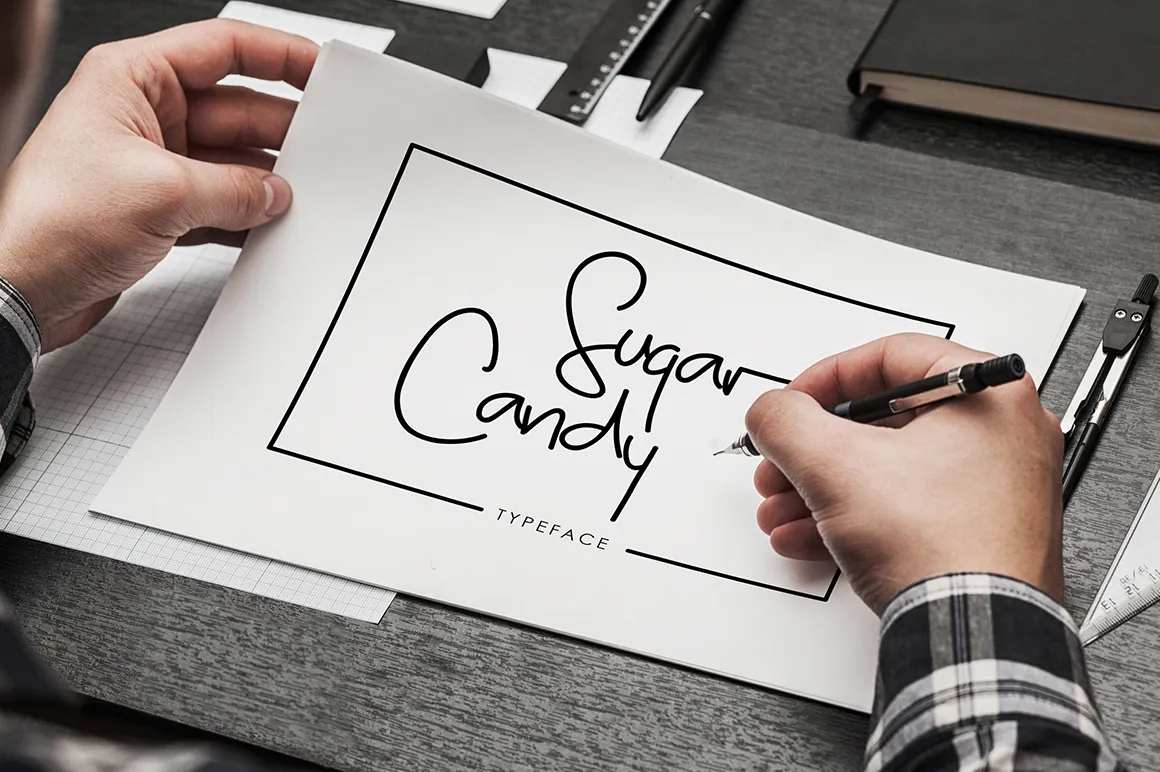
Bem-vindo à página de download para a Sugar Candy Signature Typeface! Este é um conjunto de caracteres feito à mão com uma expressividade natural que combina perfeitamente com a estética do design gráfico mais criativo e pessoal. Ideal para adicionarem um toque único aos seus trabalhos, esta fonte tem um encanto próprio que torna-a perfeita para assinaturas de e-mail personalizadas, desenhos de cartões ou até mesmo para o trabalho de design gráfico. O designer madeDeduk criou uma família de caracteres lúdicos e carismáticos inspirados nas escritas manuscritas mais amigáveis do mundo, que certamente irão enriquecer a sua tipografia com um toque especial. Esta fonte é perfeitamente adequada para quem procura adicionar alguns traços pessoais ao design de páginas web ou preservar o calor da autenticidade nas suas criações gráficas digitais. Além disso, se tiver apreciado esta fonte e quiser apoiar o autor, existem plataformas online dedicadas para quem quer dar um pouco mais. Agradecemos desde já por qualquer contribuição financeira que você possa fazer, uma vez que é muito bem-vinda.